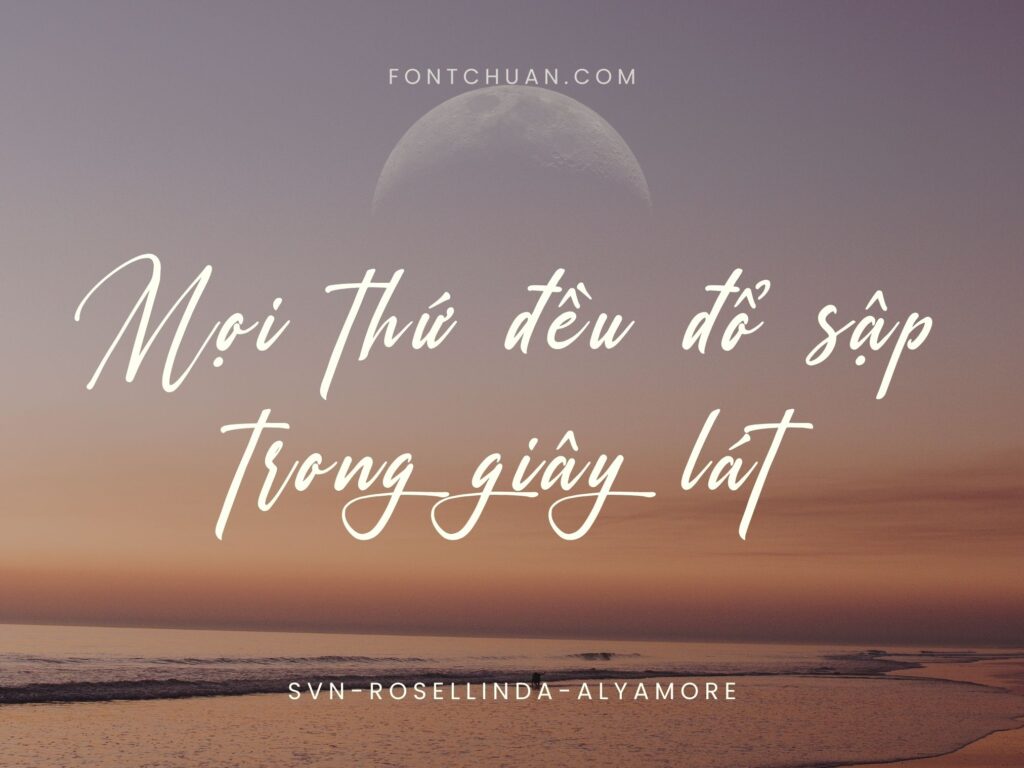
Font SVN Rosellinda Alyamore Việt Hóa
Tác giả Font: Hanief Farandi
Font SVN Rosellinda Alyamore là phiên bản Việt hóa của kiểu chữ Rosellinda Alyamore, được thực hiện bởi STYLEno.1 Fonts. Rosellinda Alyamore là một font chữ viết tay thanh lịch và tinh tế, được thiết kế bởi Hanief Farandi và phát hành bởi Hanzel Graphic. Font này nổi bật với các nét chữ mềm mại, uyển chuyển, mang đến vẻ đẹp nữ tính và hiện đại. Rosellinda Alyamore bao gồm đầy đủ các ký tự chữ hoa, chữ thường, chữ số và dấu câu, hỗ trợ đa ngôn ngữ. Font này phù hợp cho nhiều mục đích sử dụng khác nhau như thiết kế thiệp mời, logo, tiêu đề, bao bì sản phẩm và các ấn phẩm truyền thông.
SVN Rosellinda Alyamore lý tưởng cho các dự án thiết kế yêu cầu sự thanh lịch và nữ tính, như thiệp cưới, thiệp mời sự kiện, logo thương hiệu và các ấn phẩm truyền thông. Các ngành nghề như thiệp cưới, giáo dục và bất động sản có thể tận dụng font này để tạo điểm nhấn trong thiết kế. Ngoài ra, font cũng thích hợp cho các sự kiện như Tết, Valentine, Sinh nhật và các lễ hội khác.